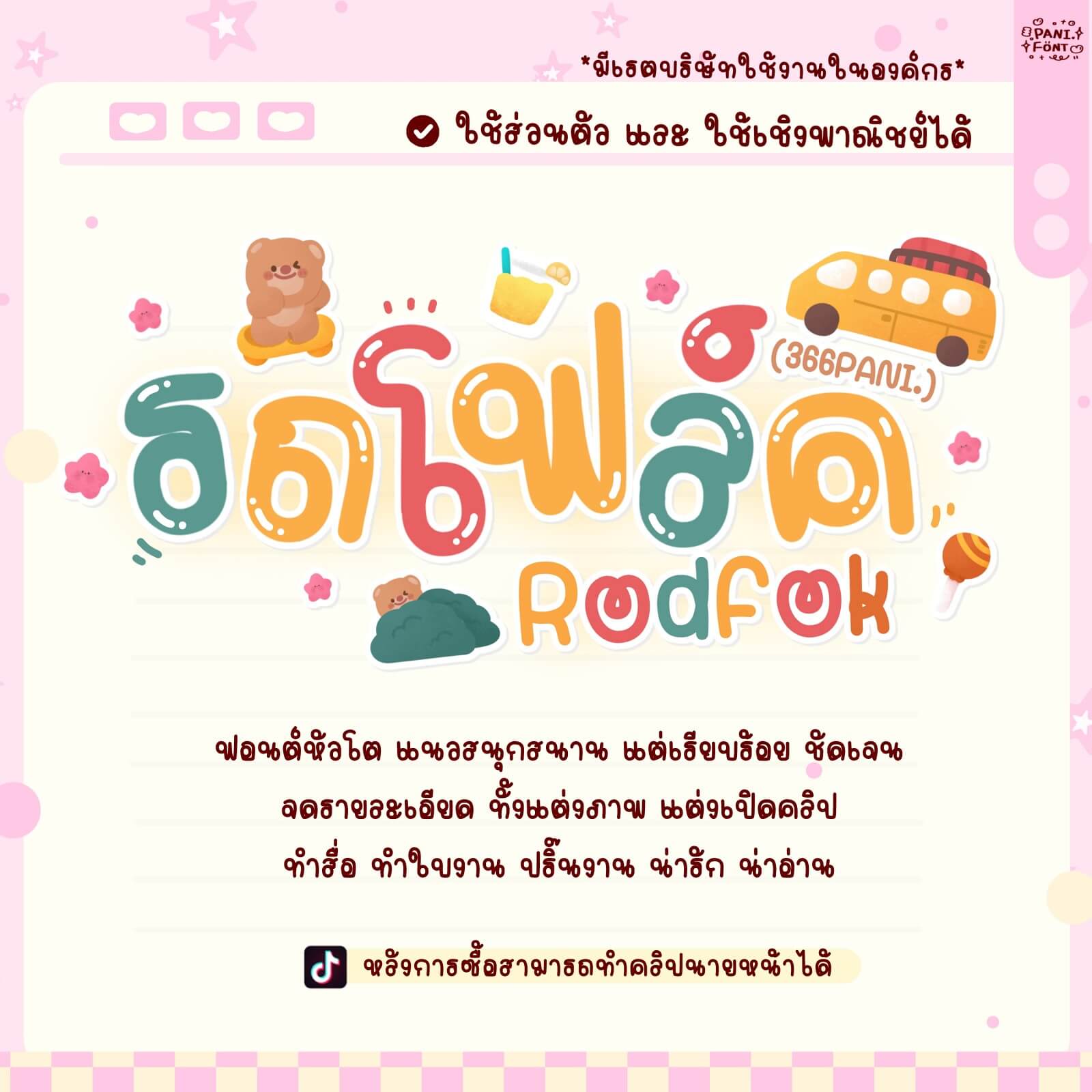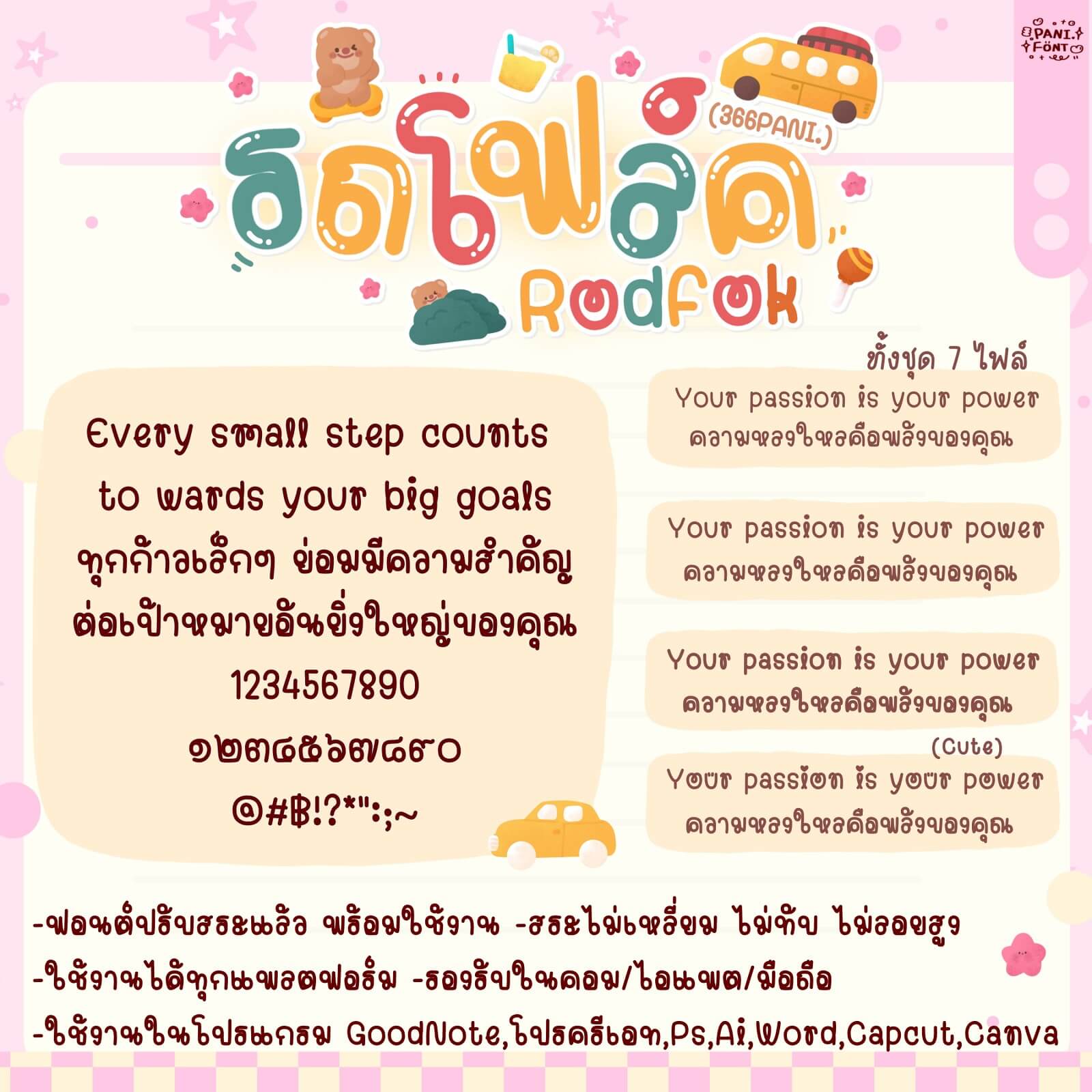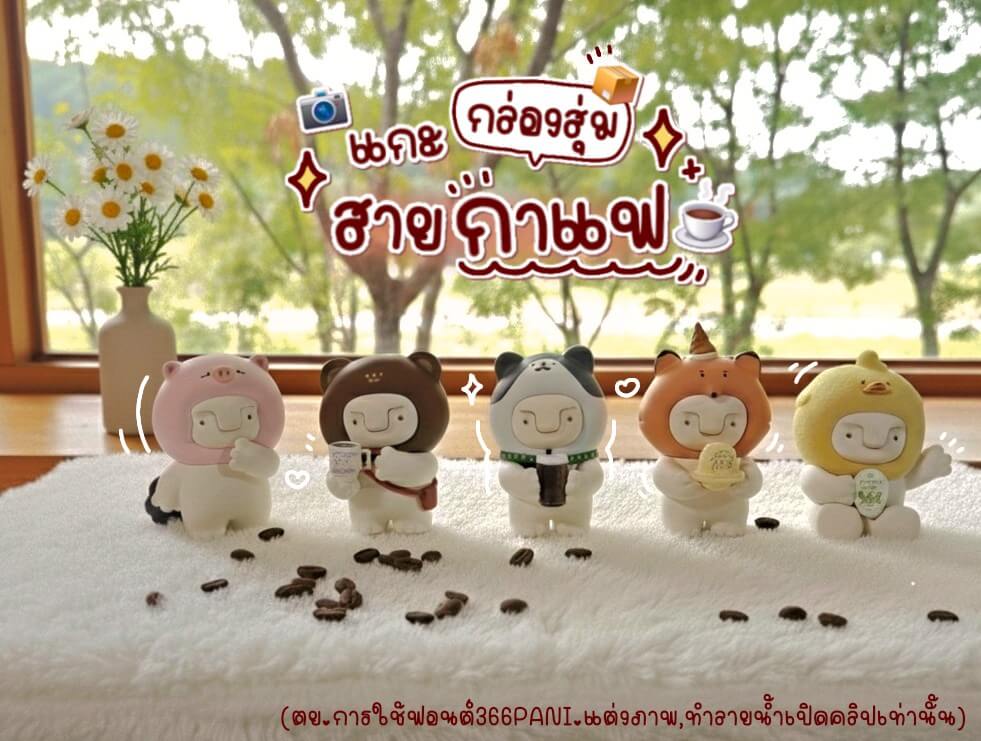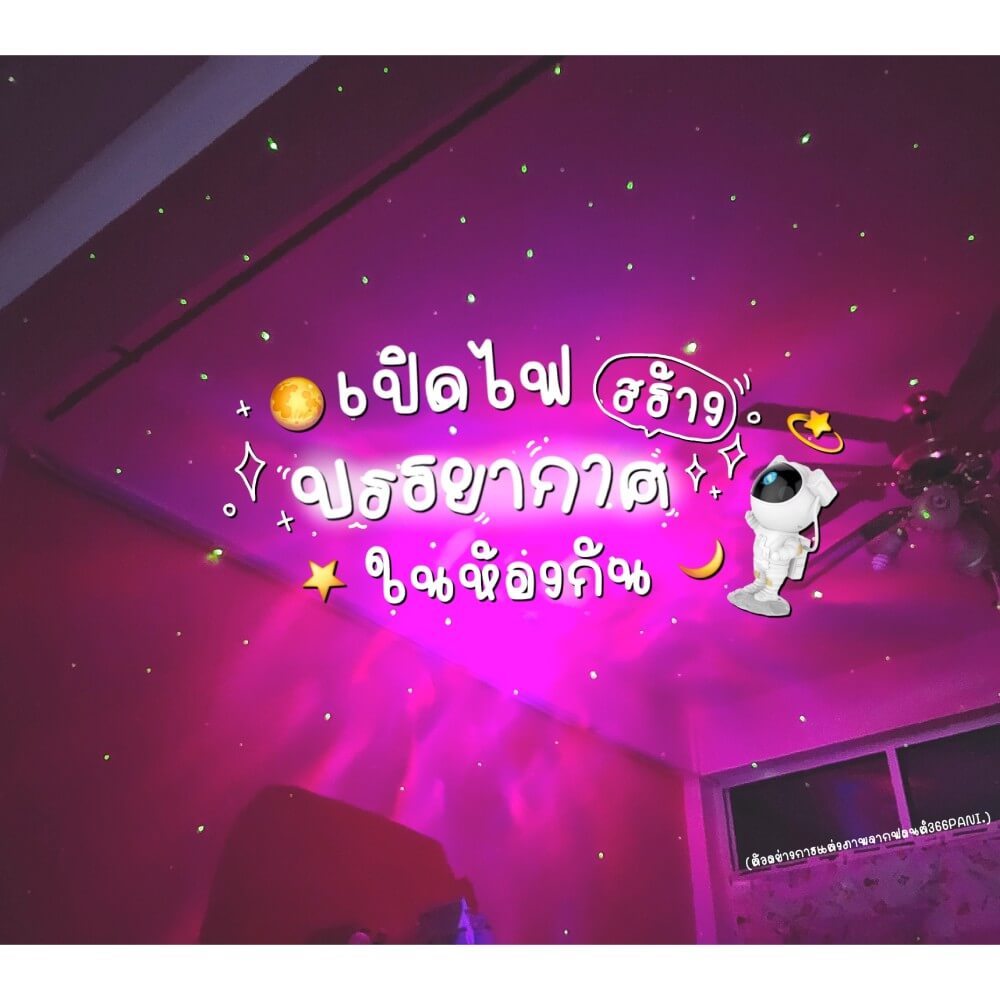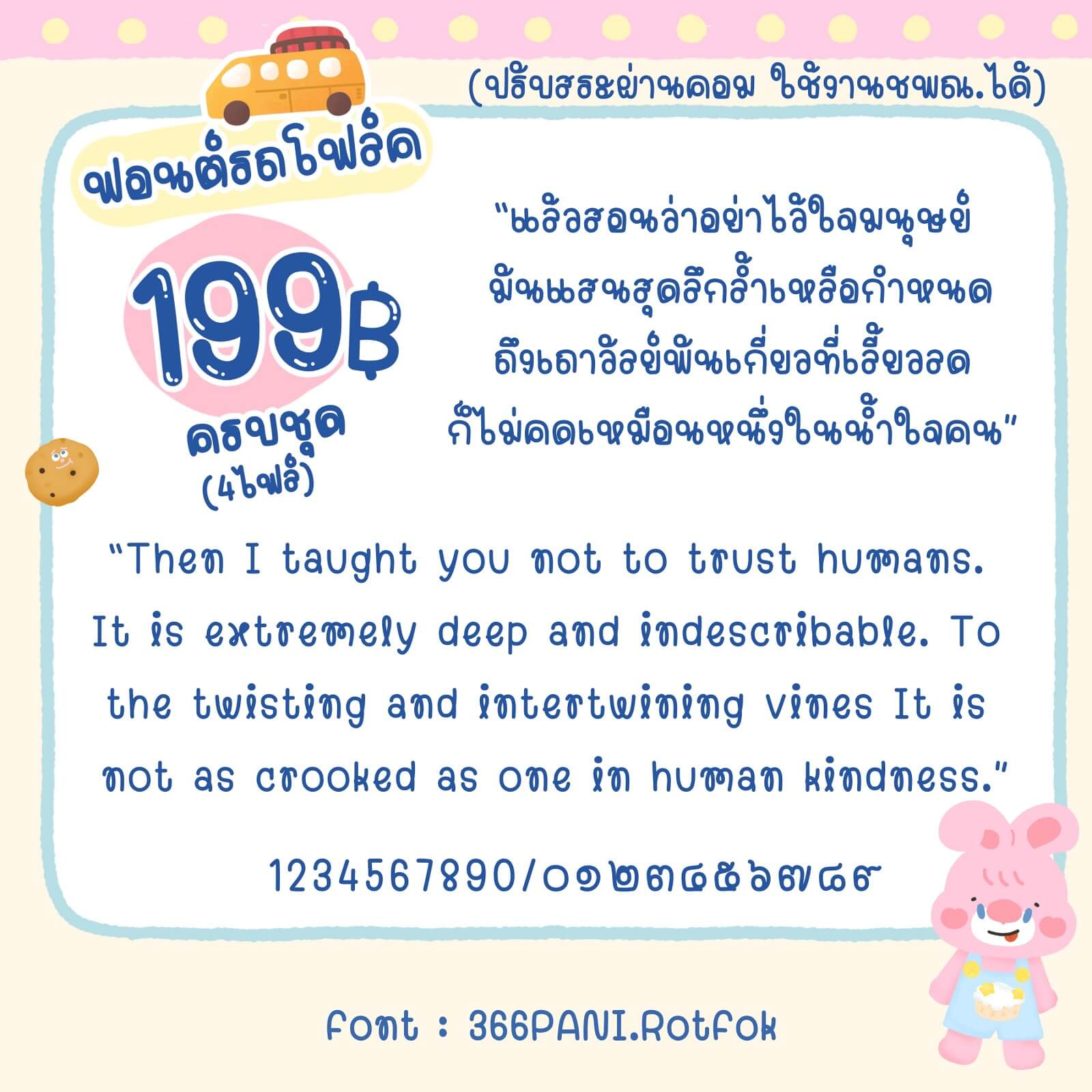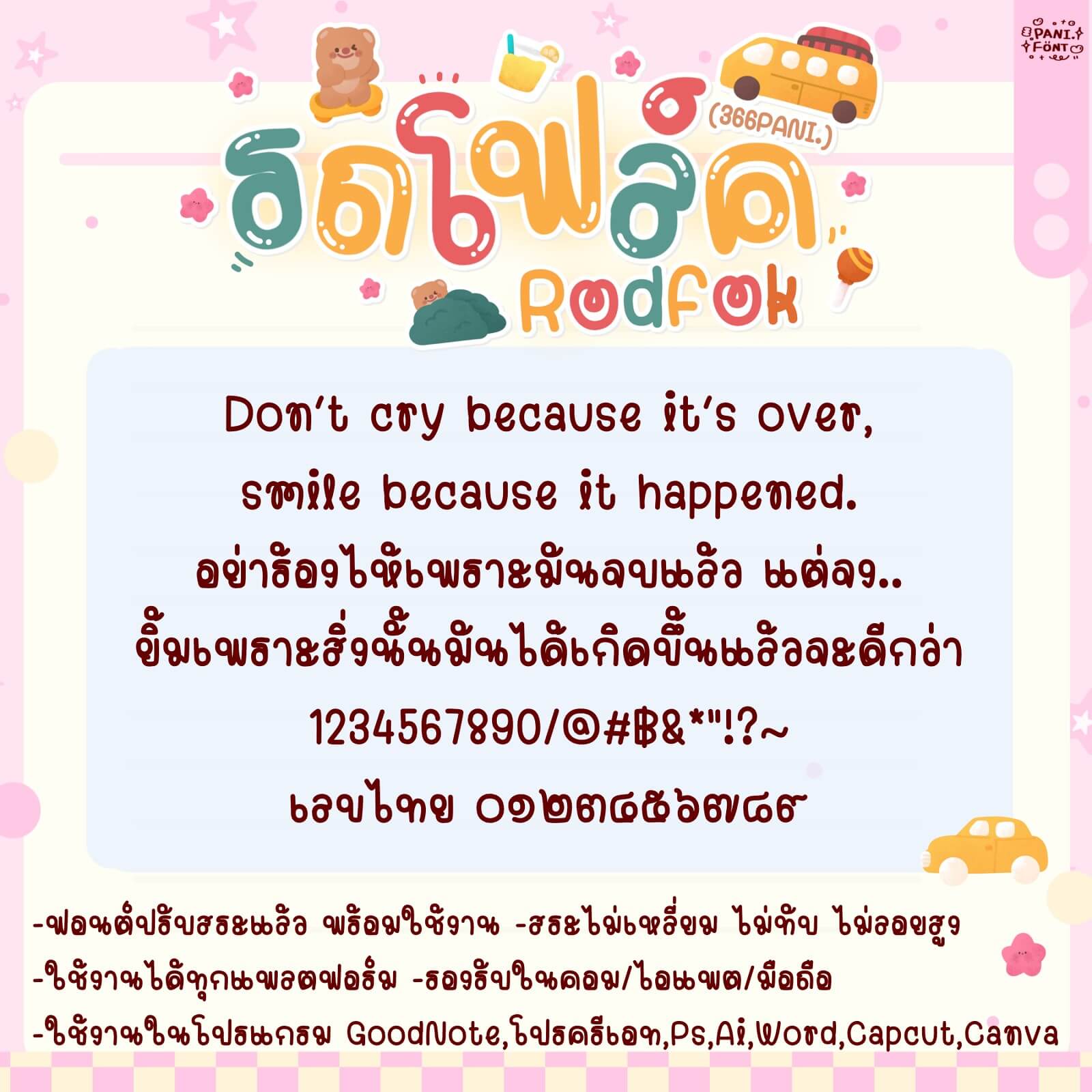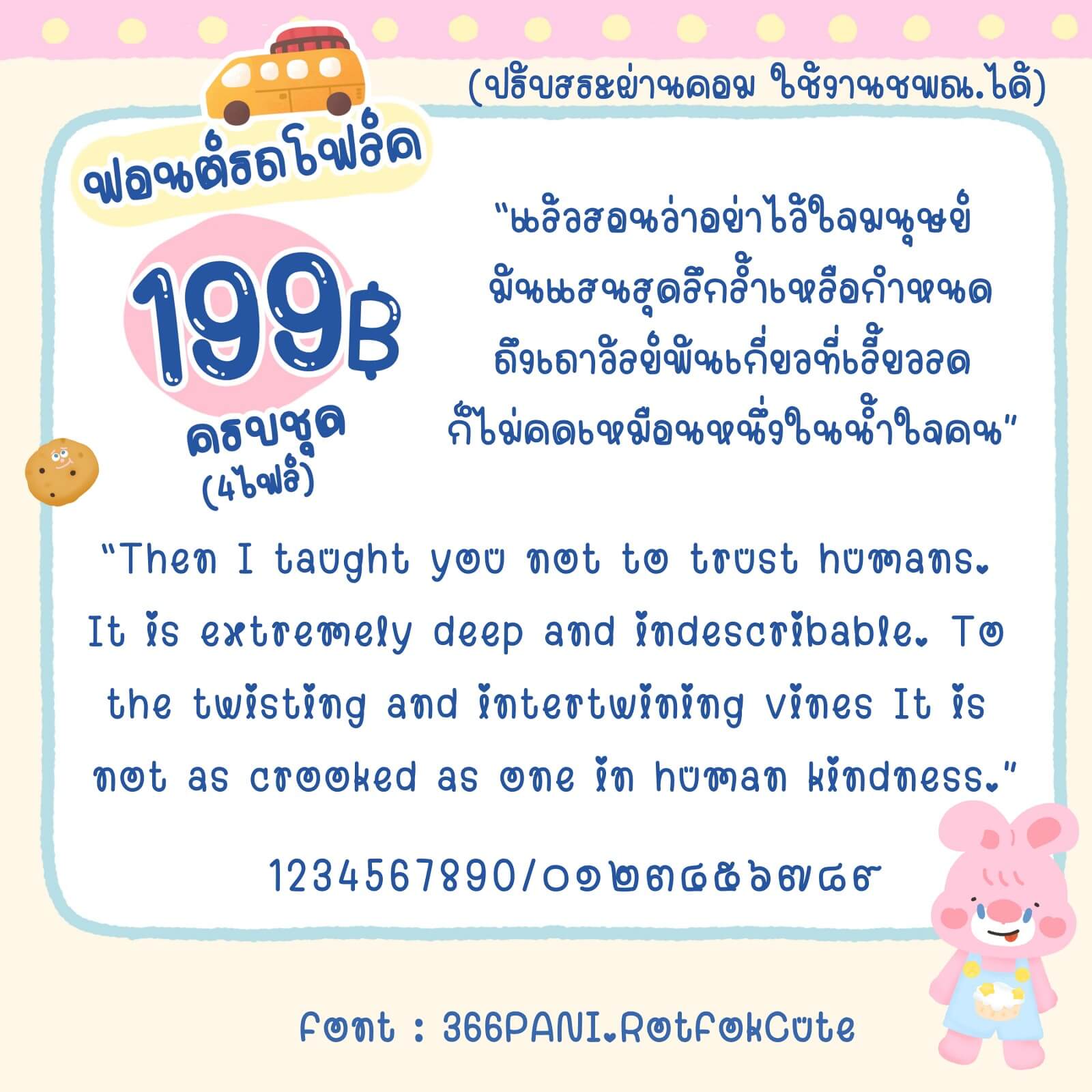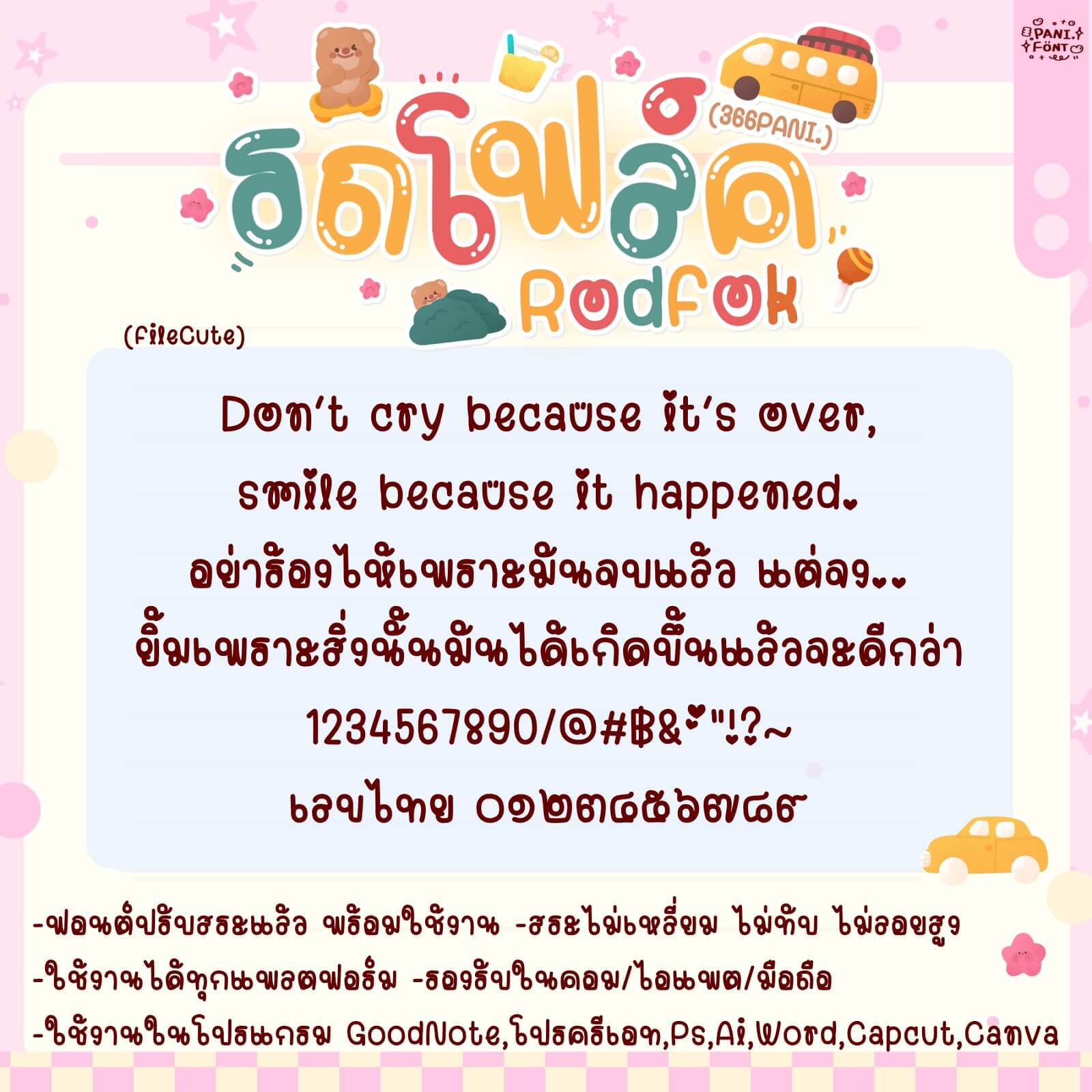
ฟอนต์ 366PANI.รถโฟล์ค – ฟอนต์หัวโต แนวสนุกสนาน แต่เรียบร้อย ชัดเจน จดรายละเอียด ทั้งแต่งภาพ แต่งเปิดคลิป ทำสื่อ ทำใบงาน พรินต์งาน น่ารัก น่าอ่าน
366PANI.รถโฟล์ค